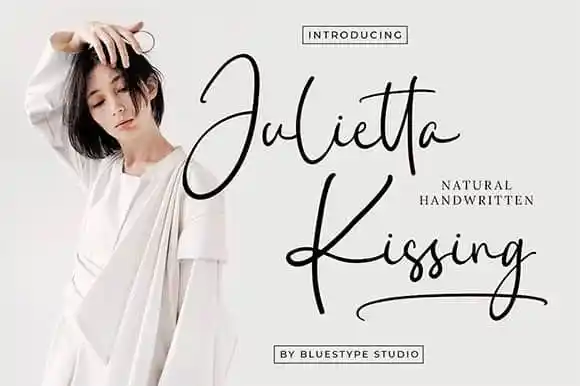
Julietta Kissing Script Font – Download Grátis
A Julietta Kissing Script Font é uma criação moderna e elegante que se mistura características clássicas e contemporâneas num mesmo tipo de letra. Esta elegante escolha de fontes é perfeita para designers criativos, desde a produção de fotografias até o design de selos empresariais e cartões de casamento. Ela é ideal tanto para trabalhos em têxteis, como slogans, moda ou marca, quanto para capas de revistas, desenhos de logotipos e assinaturas. Em suma, Julietta Kissing Script Font oferece uma versatilidade única que vai desde a estética vintage até as tendências atuais, tornando-se uma fonte indispensável para qualquer designer gráfico ou criador de conteúdo que valoriza um toque único e sofisticado em seu trabalho.